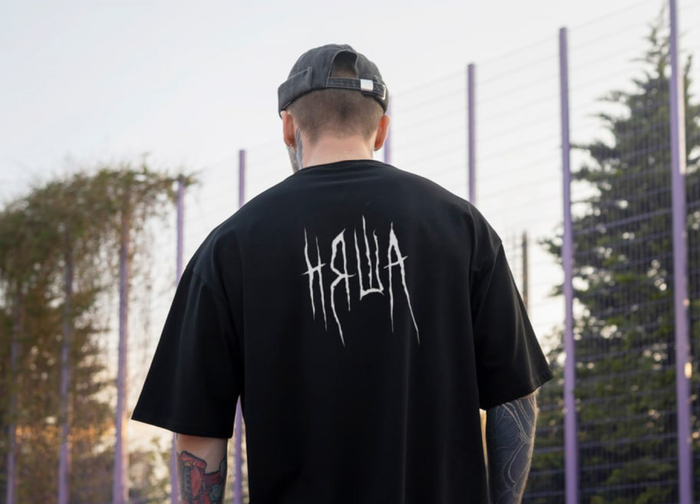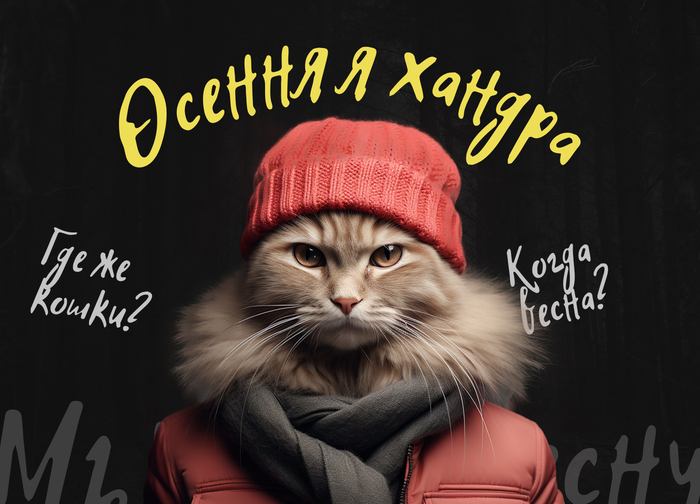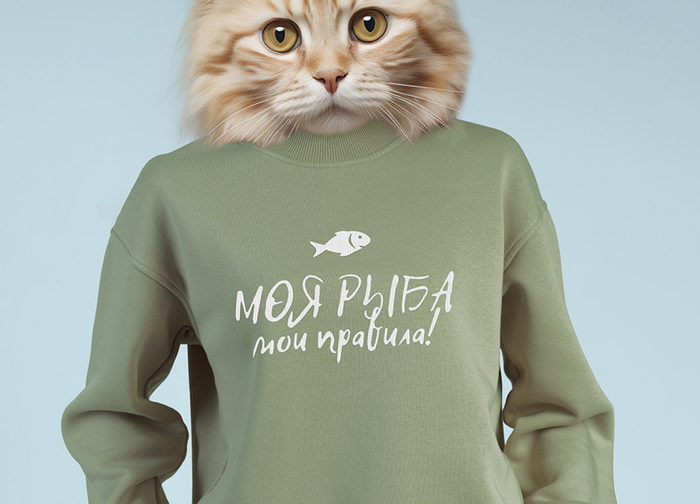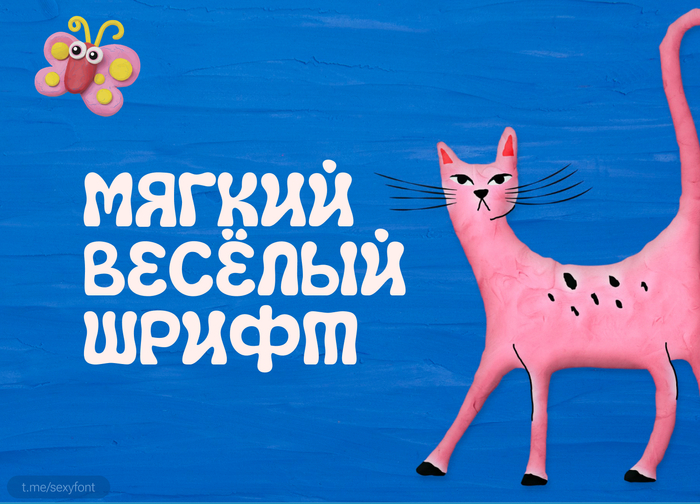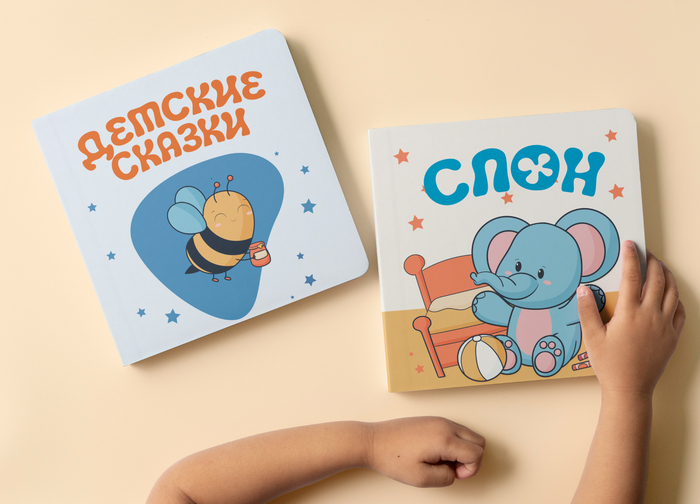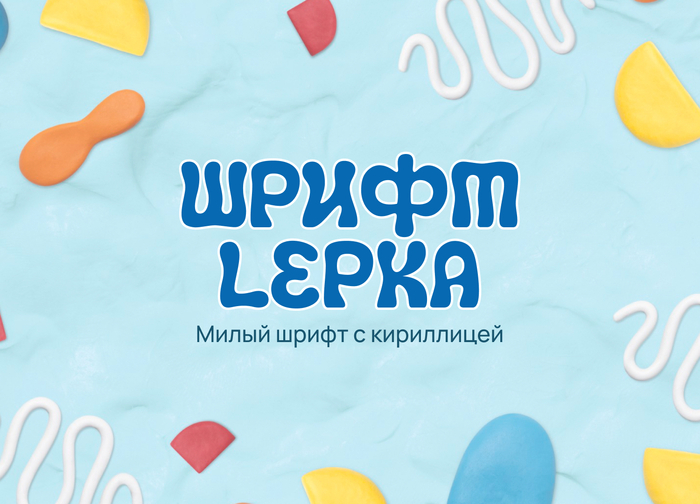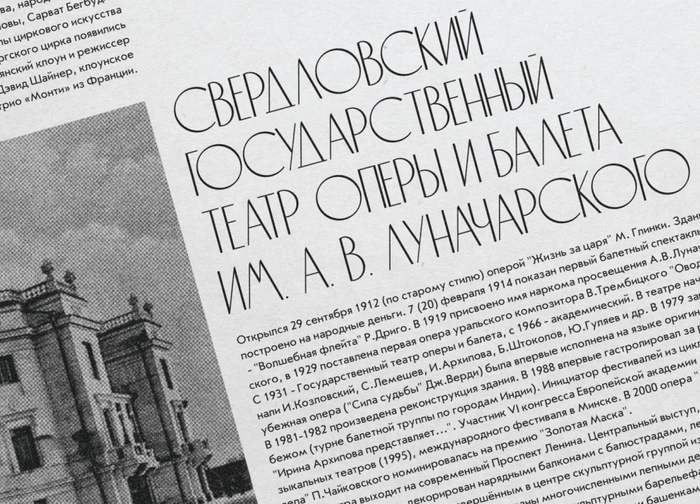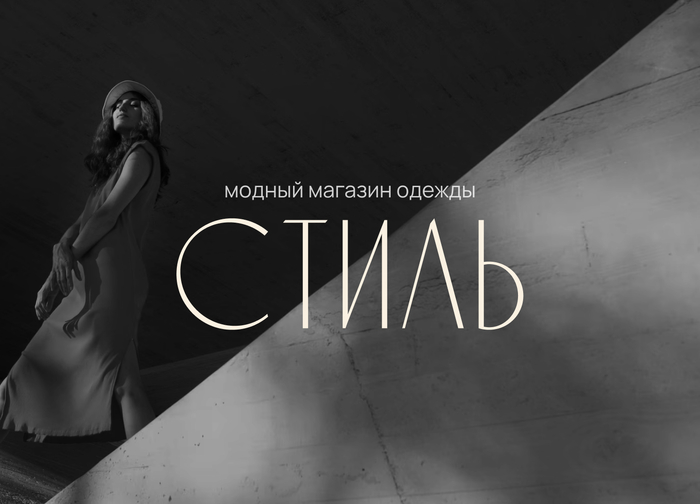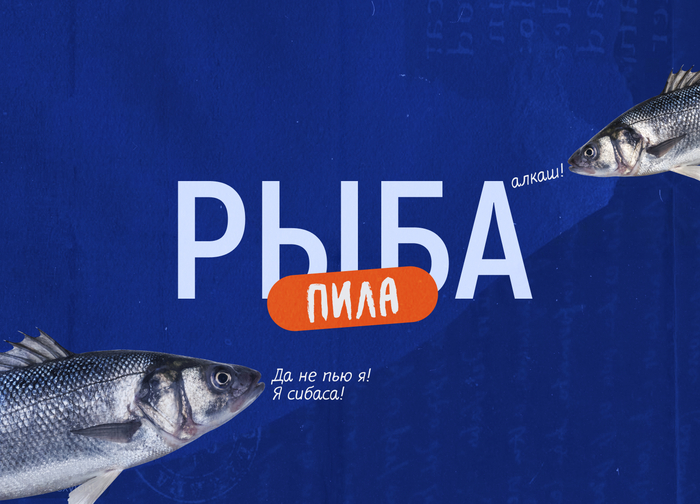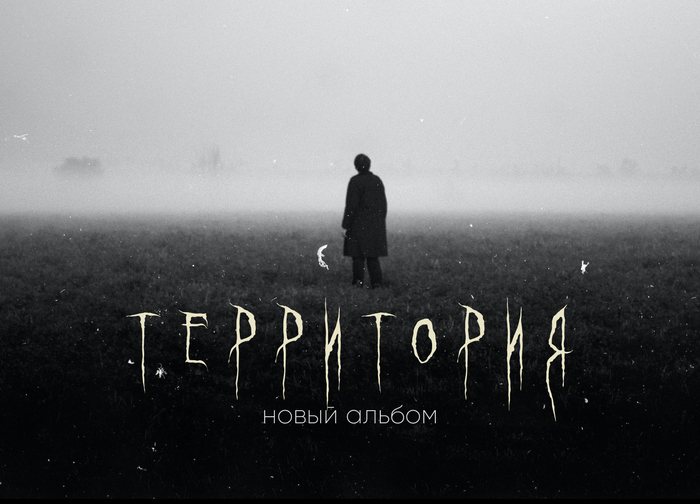
Кириллические шрифты
Бесплатный шрифт molot
Мощный, тяжёлый шрифт Molot. Сделал такую вот презентацию белочки с орешком. Уверен ты найдешь ему применение.
Шрифт flow
Привет друзья) Доделал новую презентацию. Шрифт Flow. Кириллический рукописный. Идеально для создания заметок)
Шрифт Sverdlovsk
Старенький, но все же моднявый кириллическийшрифт. Презентацию частично сохранил от автора. Она в целом хороша. Почему то я был уверен, что публиковал его) Но не нашел в своем архиве.
Пластилиновый шрифт. Лепка
Шрифт lepka. Милый шрифт в виде лепнины из пластилина) идеально для для детских тематик.
Шрифт Hitch-hike. Кириллический шрифт
Подходит для плакатов, открыток, социальных сетей, обложек и других креативных проектов. На нашел ни лицензии, ни в продаже) Ни личный контакт автора. Автор: Annastasia Samsonova
Зомби шрифт Ghastly panic
Ghastly panic. А давненько не выкладывал страшненькие зомби-шрифты. Вот держите, распишитесь. Лучше в максимально коротких словах использовать. Читаемость на грани)
Шрифт gropled. Кириллица
Gropled отлично подходит для создания логотипов, типографики для веб-дизайна, дизайна плакатов и многого другого! Почти всю презентацию сохранил от автора.
Старый добрый akrobat. Шрифт
Высокий и в меру вместительный шрифт. За это его и полюбили). Не баян, а классика. Я должен был сделать для него презентацию.